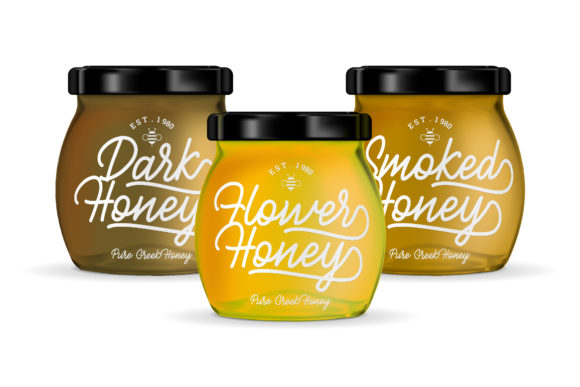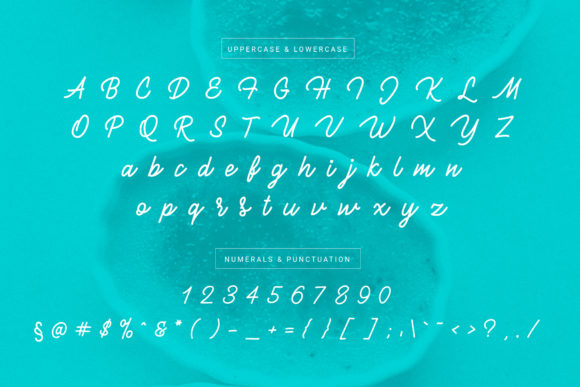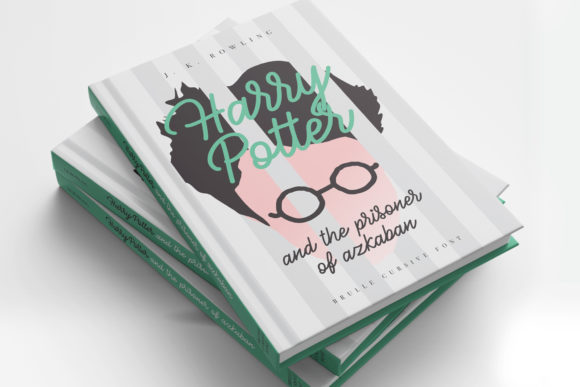
Brulle Font
Brullee est un scénario doux et époustouflant avec des lettres incroyables. Utilisez-le pour transformer n’importe quel projet de conception en un véritable objet remarquable !